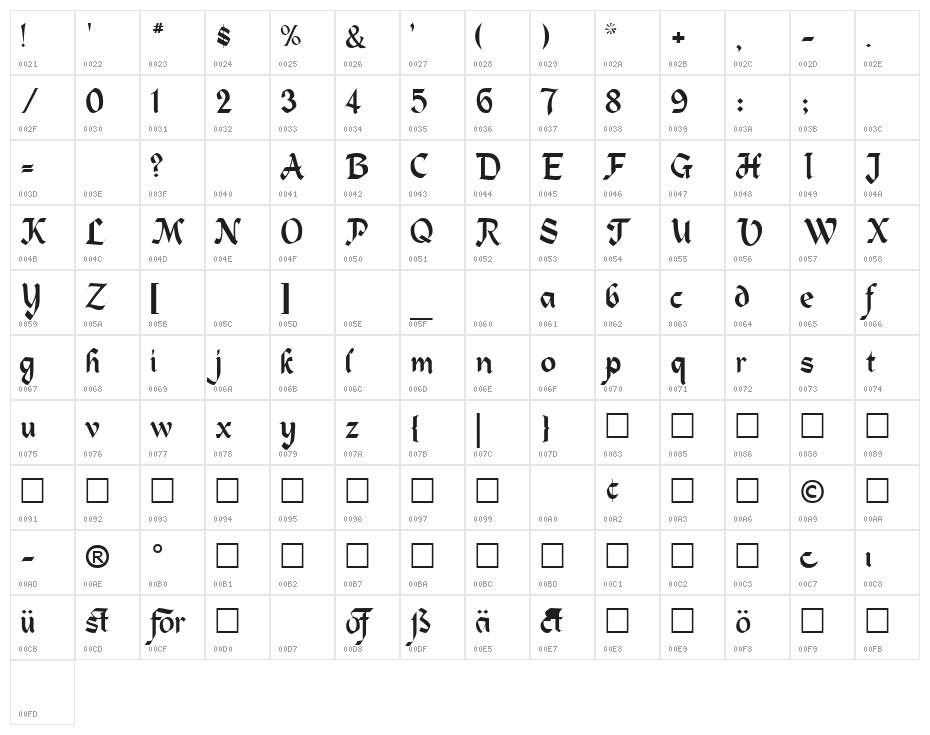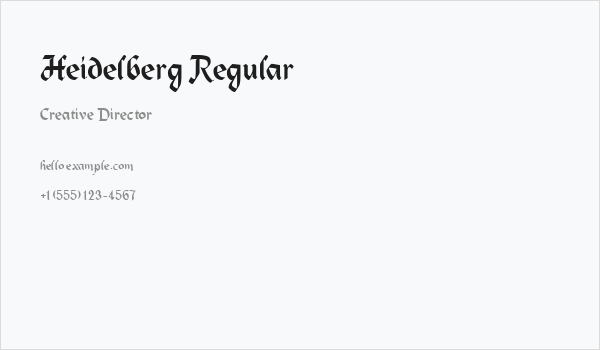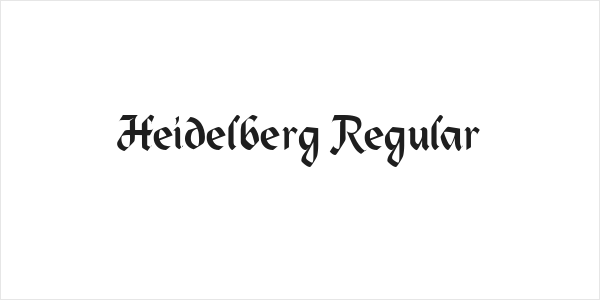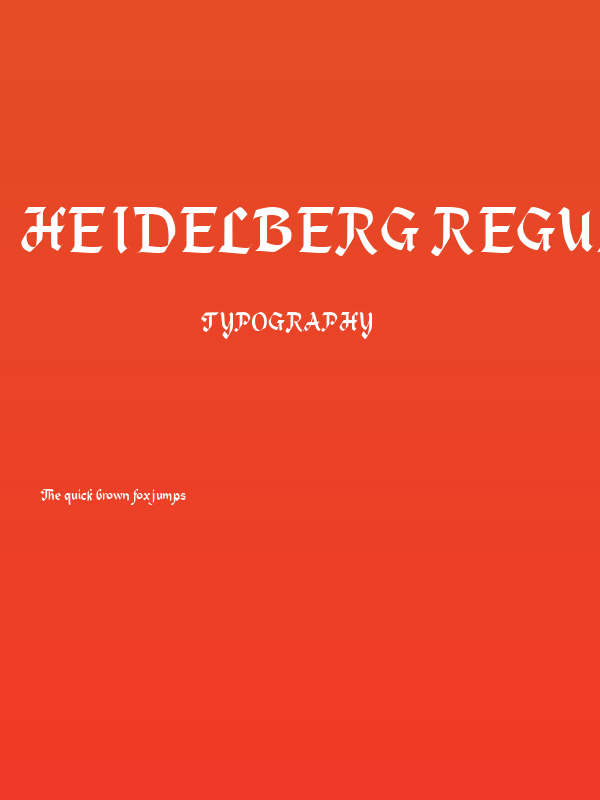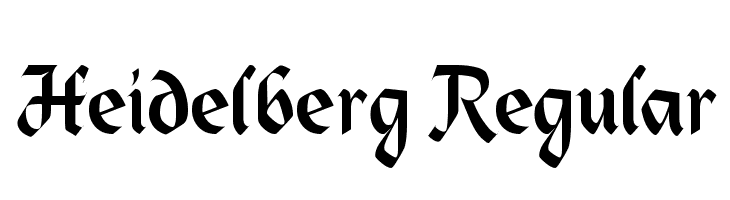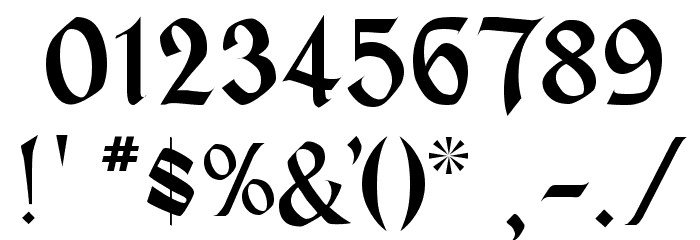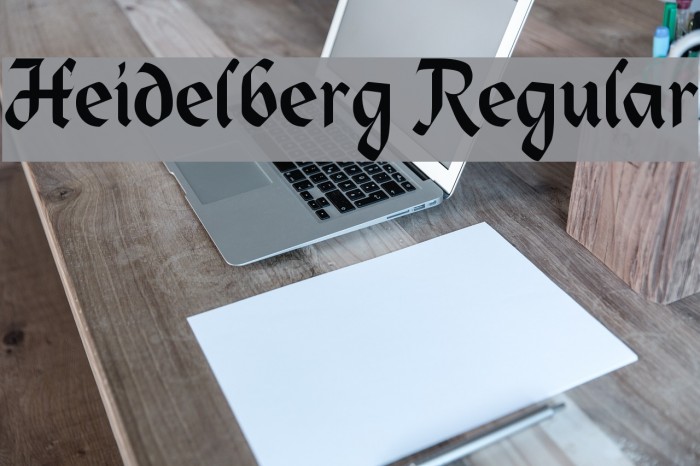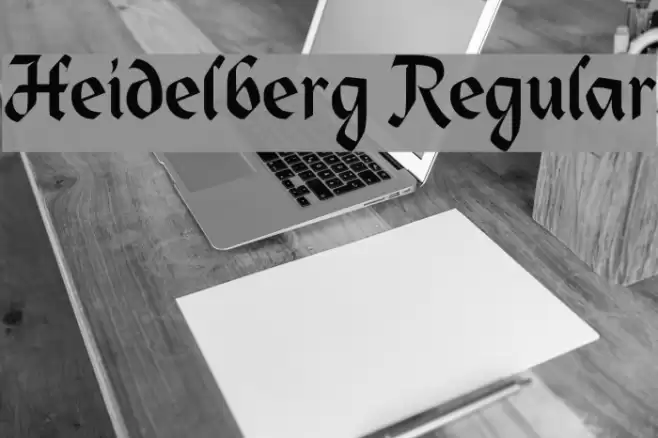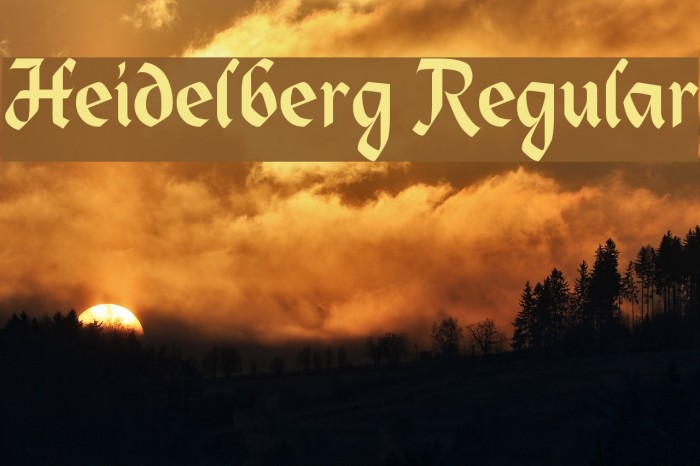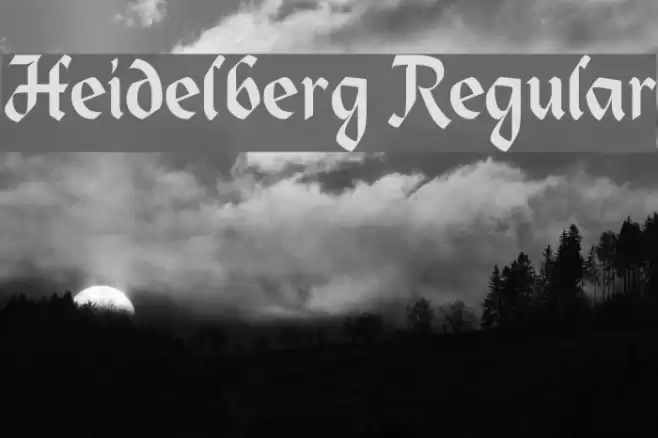
Heidelberg Regular Font
| Caso de uso | Headlines, Logos, Decorative text |
| Projetos propostos | Ideal for historical documents, invitations, certificates, or any project requiring a traditional Gothic touch. |